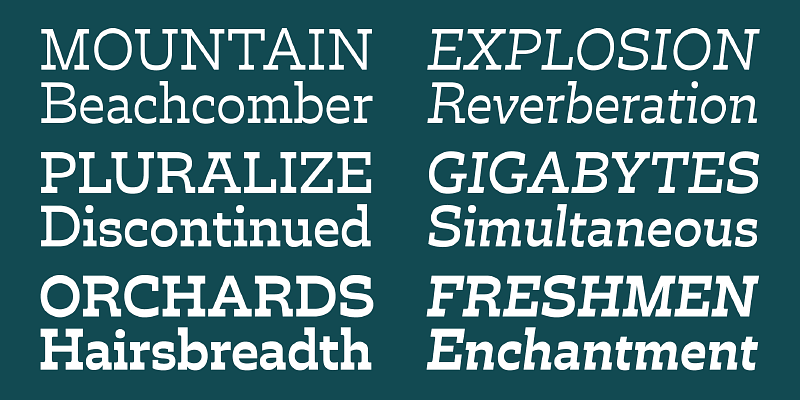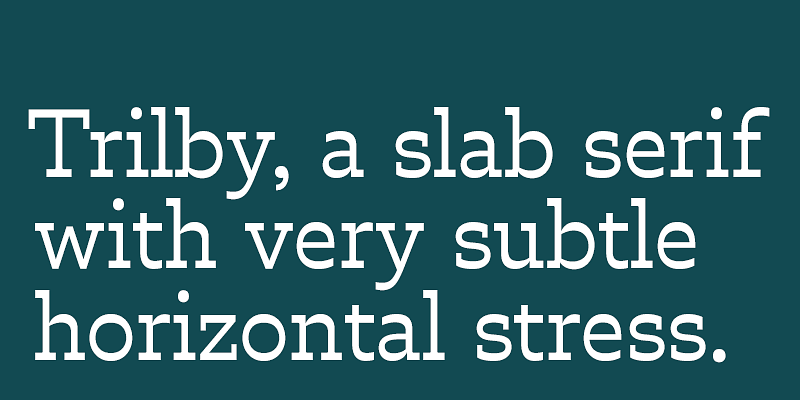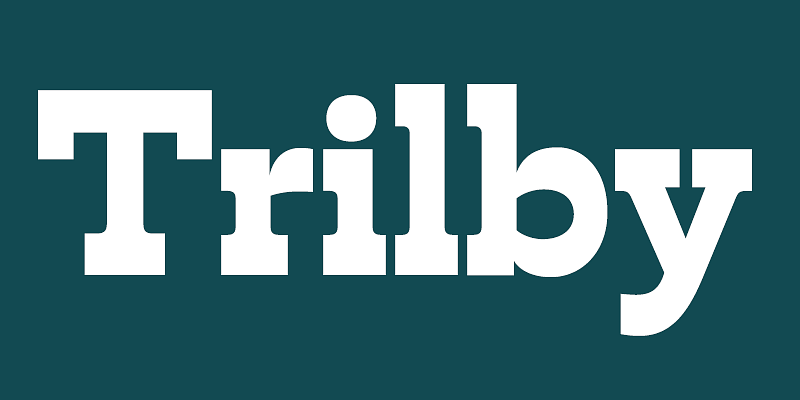
型破りなリバースストレスを特徴とする 19 世紀の「French Clarendon」は、同時期のビクトリア朝書体である、スラブセリフ体の Antique やサンセリフ体の Grotesque のような汎用性は備えていません。「Trilby」は、David Jonathan Ross がこの乱暴なスタイルを整え、そのフォーマルなエッセンスを育んだ書体です。過剰な装飾を排除した「Trilby」は、単なる目新しさを超えて、オフビートな魅力と繊細なウィットを備えた、きわめて有用な現代的デザインとなっています。
David Jonathan Ross は、カスタム書体や小売り用書体デザインに使うあらゆる形と大きさの文字をマサチューセッツ西部の森にある自分のスタジオで作成しています。ロサンゼルス出身の彼は、Hampshire College で書体作りを始め、2007 年に The Font Bureau に入社してベジェ曲線の扱いの腕前を磨きました。現在は、自社である DJR で書体デザインを公開するかたわら、Type Network を使ったプロジェクトや、Font of the Month Club 向けの珍しい表示用書体の開発に取り組んでいます。